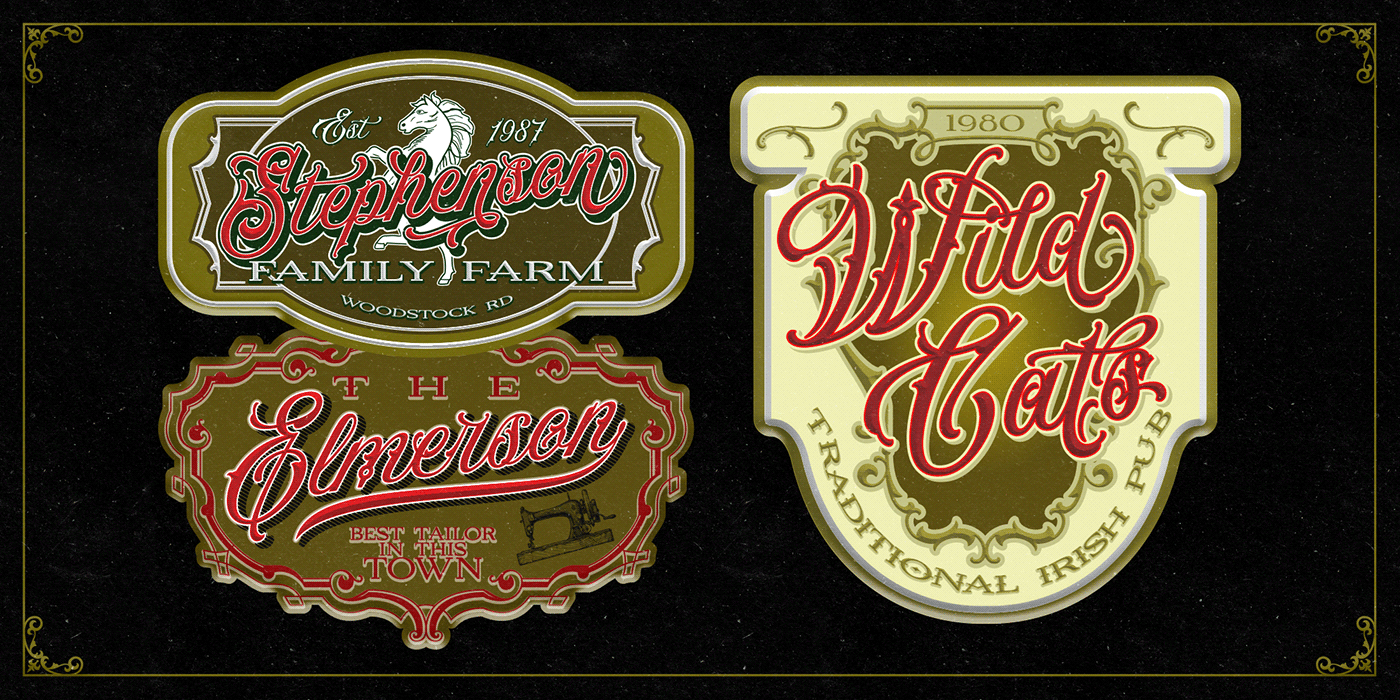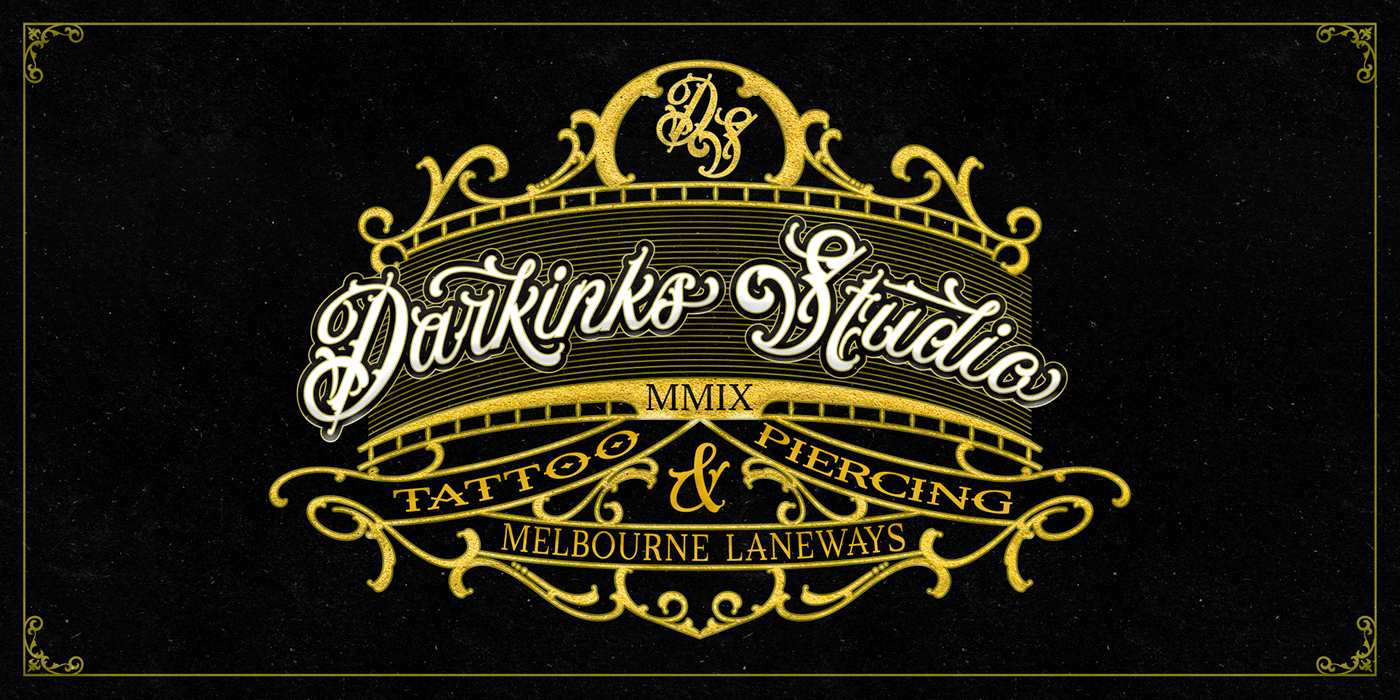
Sketchson Font Family
Description de Sketchson Font Family
Sketchson est une police de typographie vintage esthétique, contenant du script, des empattements et des empattements larges. Inspiré du passé, signalisation élégante, art à la feuille d’or, peinture d’enseignes, lettrage, tatouage, logo et ancienne étiquette. Sketchson Script est livré avec des tonnes de caractères alternatifs et une minuscule alternative spéciale (i) est un swash de fin qui rend plus attrayant pour les yeux et Sketchson Serif est une police d’appariement à combiner dans votre conception. enfin BOUM..!! vous obtenez un superbe design pour votre projet.